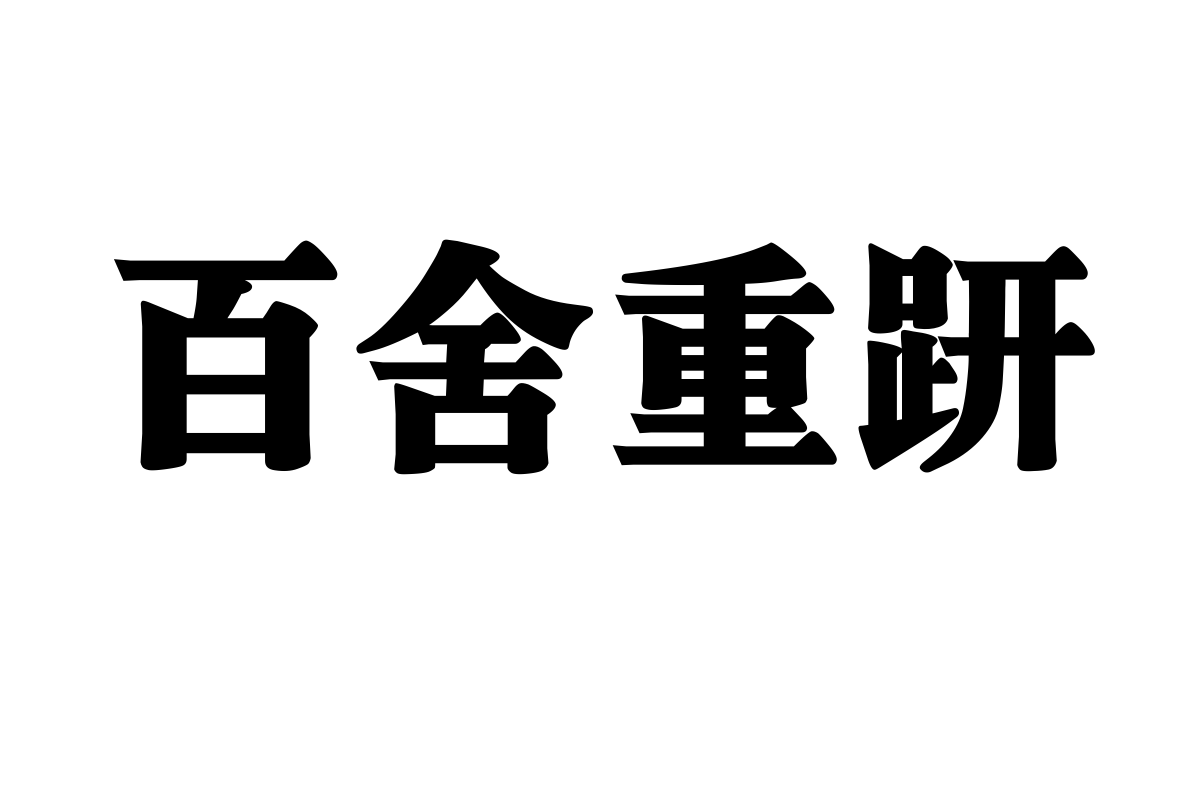
汉仪超粗宋简是一款具有独特设计风格的字体,它结合了现代感和传统元素。这款字体的特点是笔画粗细不一,给人一种强烈的视觉冲击感。它的字形结构紧凑,笔画流畅,给人一种简洁明了的感觉。同时,它也具有一定的艺术性,能够吸引人们的注意力。
这款字体适用于各种设计场景,如海报、广告、宣传册等。它可以为设计作品增添一种独特的风格,使其更具吸引力。无论是商业还是个人项目,都可以使用这款字体来提升设计的美感和品质。